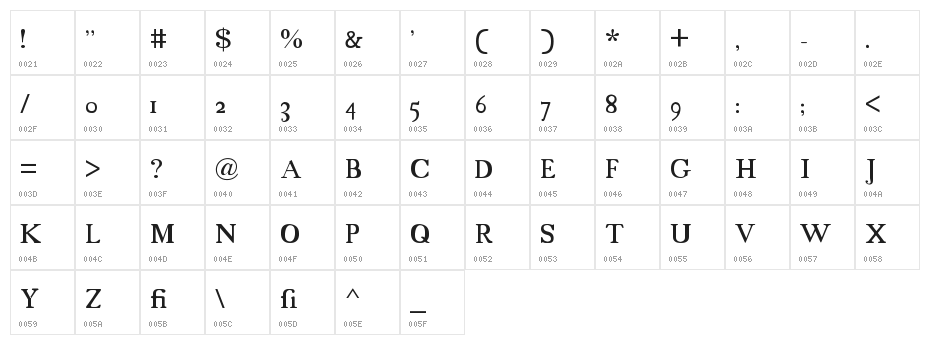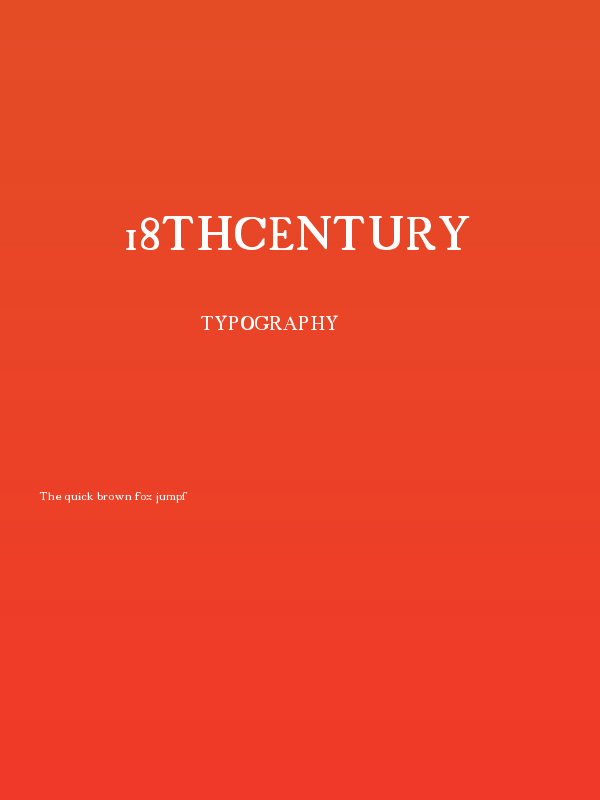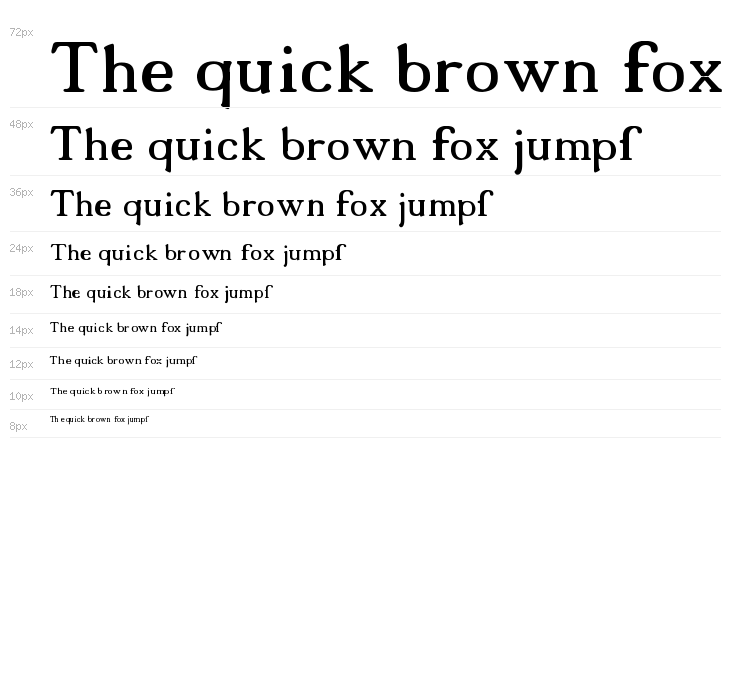
18thCentury Font
| Progetti proposti | This font is perfect for projects that require a touch of elegance and tradition, such as wedding invitations, historical publications, or luxury branding. |